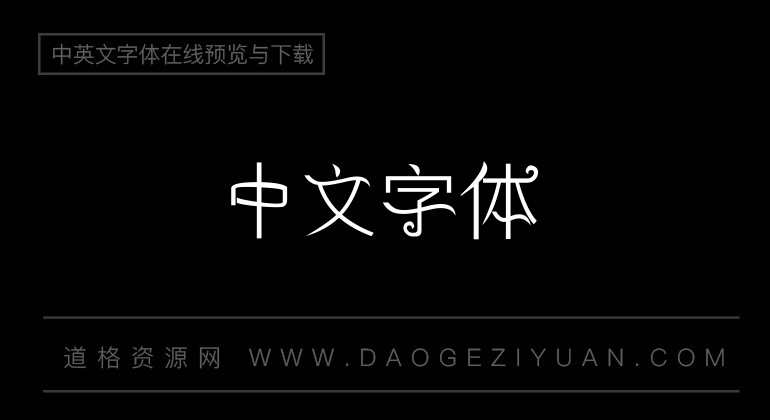
? 逐浪花体是一款日文字体,由日本设计师梅本英明设计,于2012年发布。这款字体以柔和的线条和清新的设计风格著称,以植物为灵感,充满活力和柔和的色彩。它的特点是圆润的线条,简洁优雅,适合用于海报、书籍封面、商业广告等。文件名:ZhuLangHuaTi-2.otf
逐浪花体是一款非常不错的手写艺术字体,具有很好的视觉感,适合于文化类的宣传设计、商业类品牌的广告和产品包装设计以及个性化文字排版等较多场景。